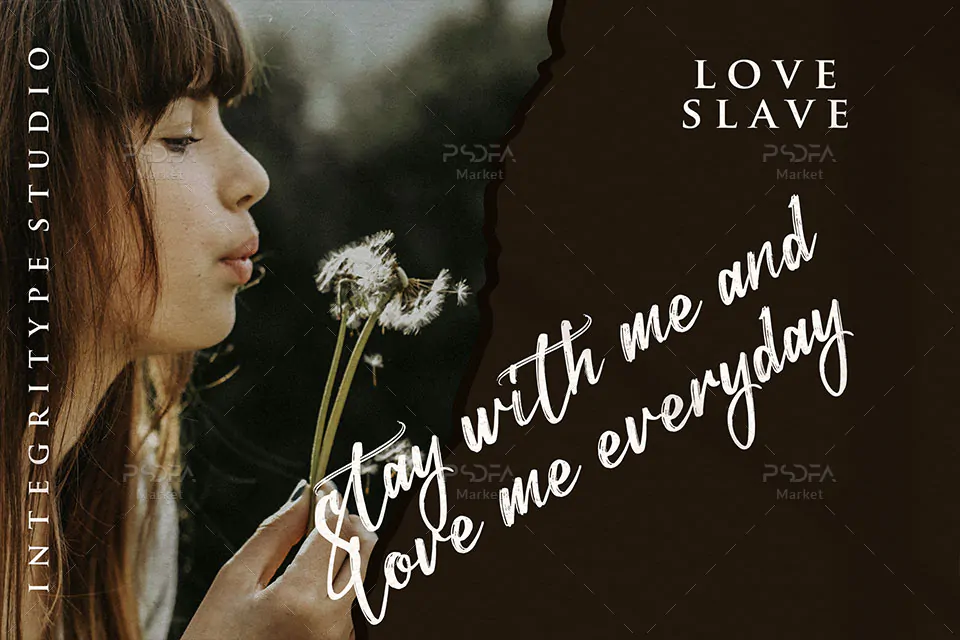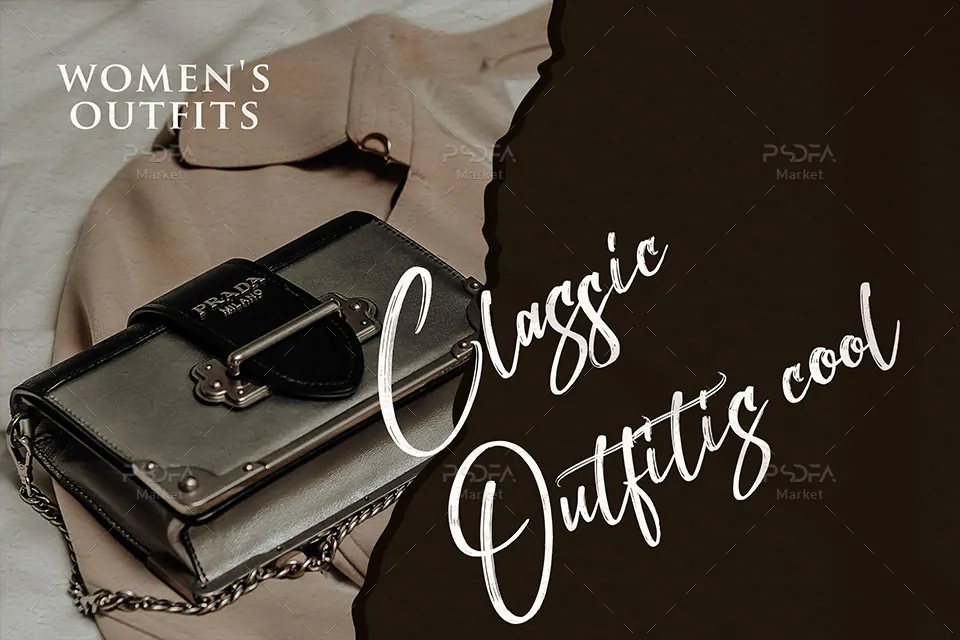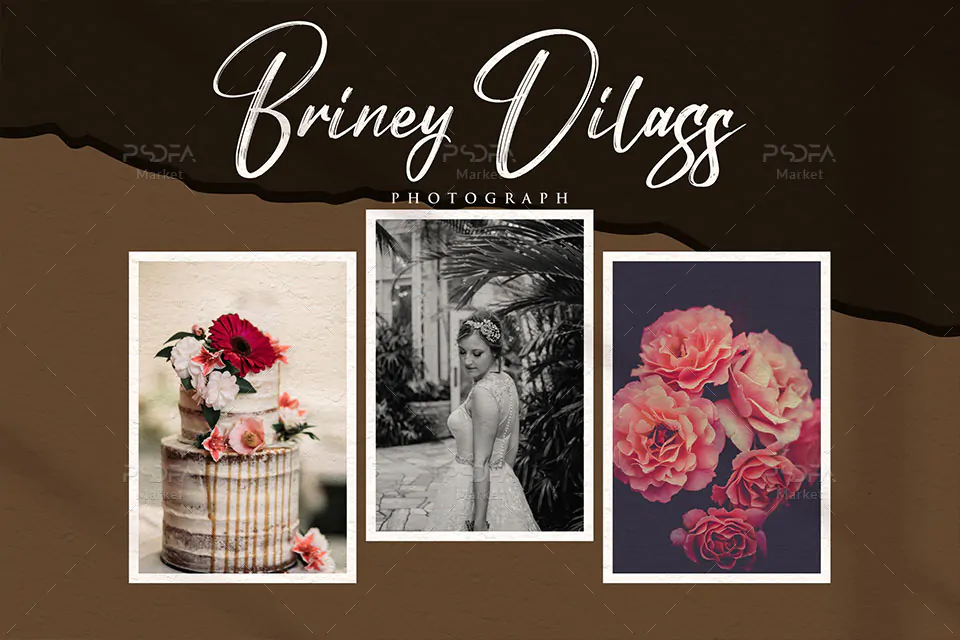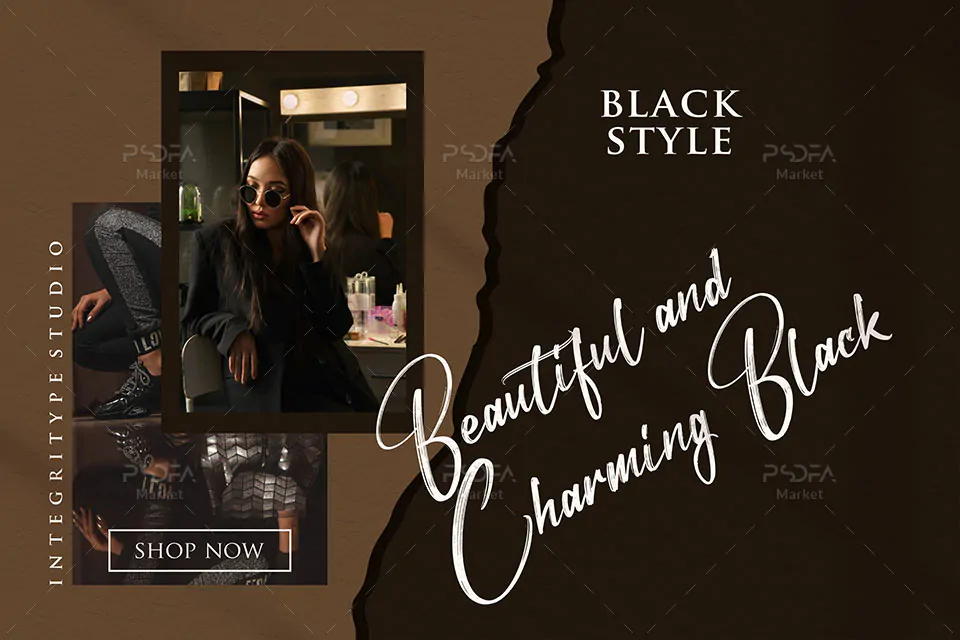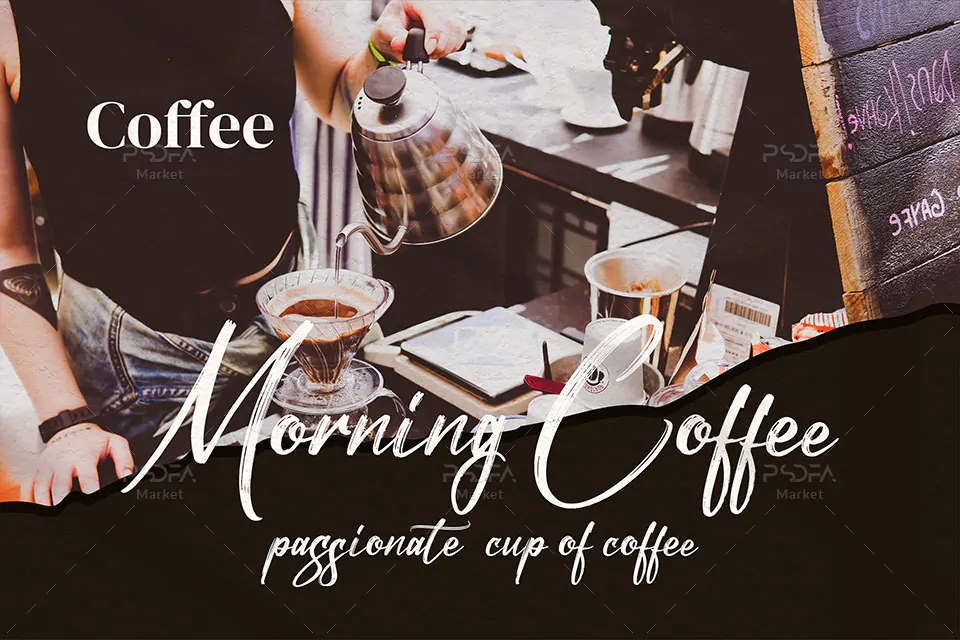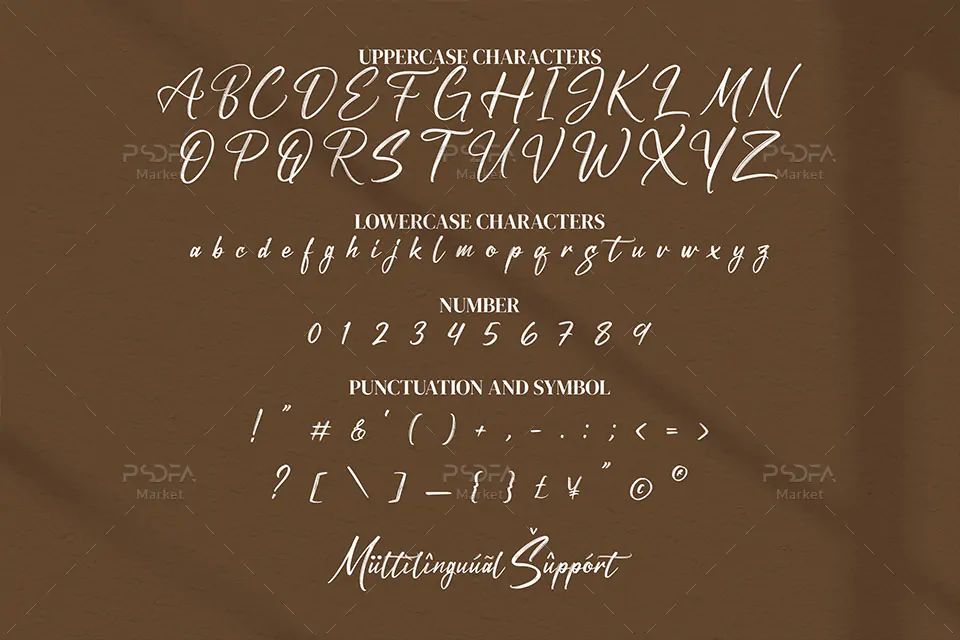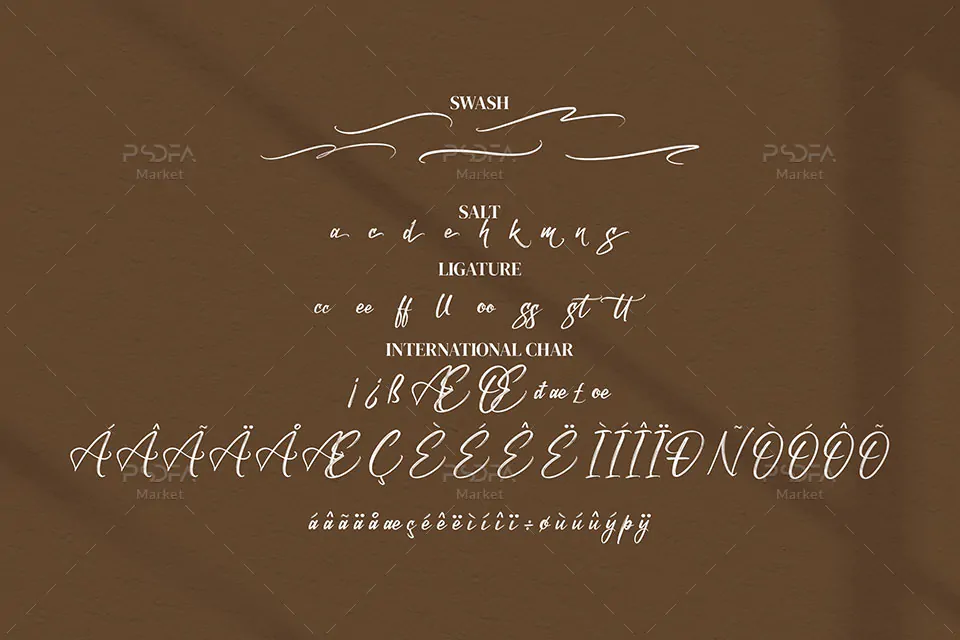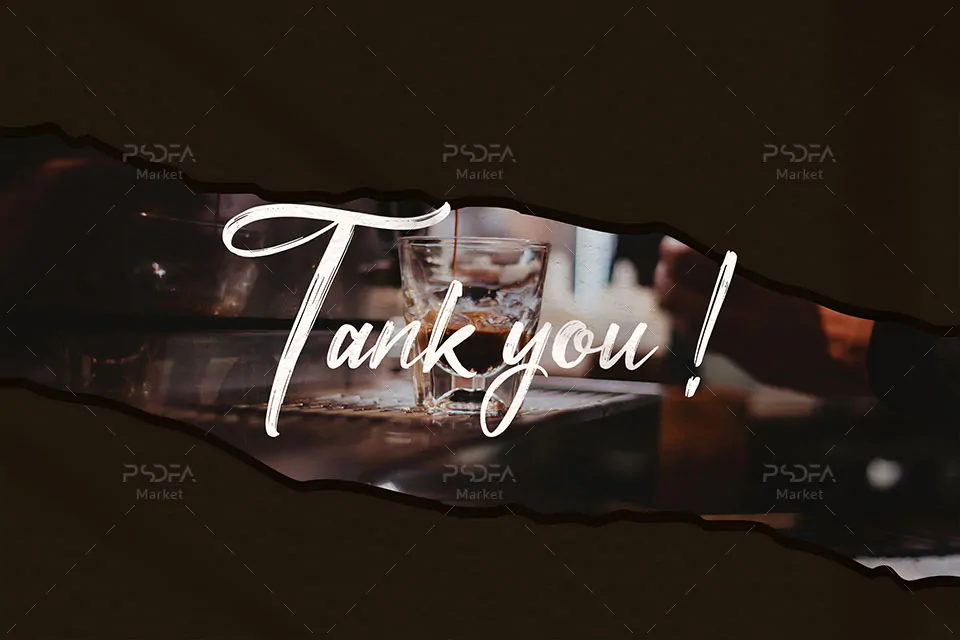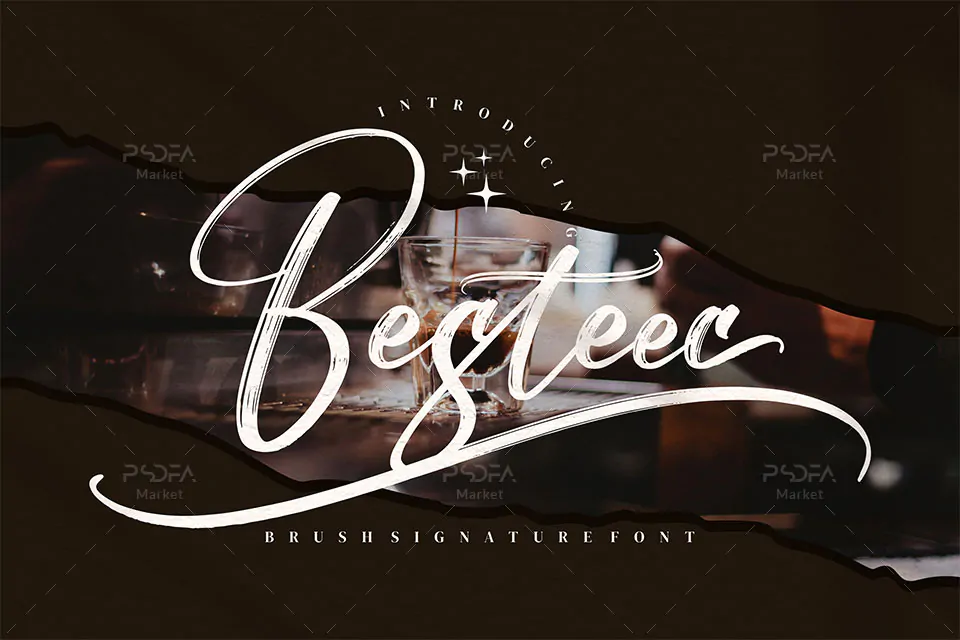
اسکریپت فونت دستنویس و قلمویی Besteec یک قلم فوق العاده زیبای انگلیسی است که با کارکترهایی باریک طراحی شده و مناسب جهت استفاده در طرح و پروژههای گرافیکی مختلف به خصوص طراحی انواع پوستر میباشد. این فونت زیبا در قالب فایل OTF, TTF در فایل محصول قرار دارد که با نصب یکی از این 2 فرمت در پوشه فونتهای سیستم میتوانید از این فونت انگلیسی در تمام نرم افزارهای گرافیکی و تایپ متون همچون فتوشاپ، افتر افکت، پریمیر، ورد، پاورپوینت و … استفاده کنید.
فونت دستنویس و قلمویی Besteec در وزن معمولی (Regular) و مورب (Italic) طراحی شده است که میتوانید از آن در طراحی انواع پوستر، بسته بندی محصولات، لوازم التحریر، بگهای خرید و هدیه، ظروف یکبار مصرف، تقویم، بنر، بروشور، تراکت و دیگر طرحهای گرافیکی استفاده کنید.
- نام فونت: Besteec
- وزن: Regular, Italic